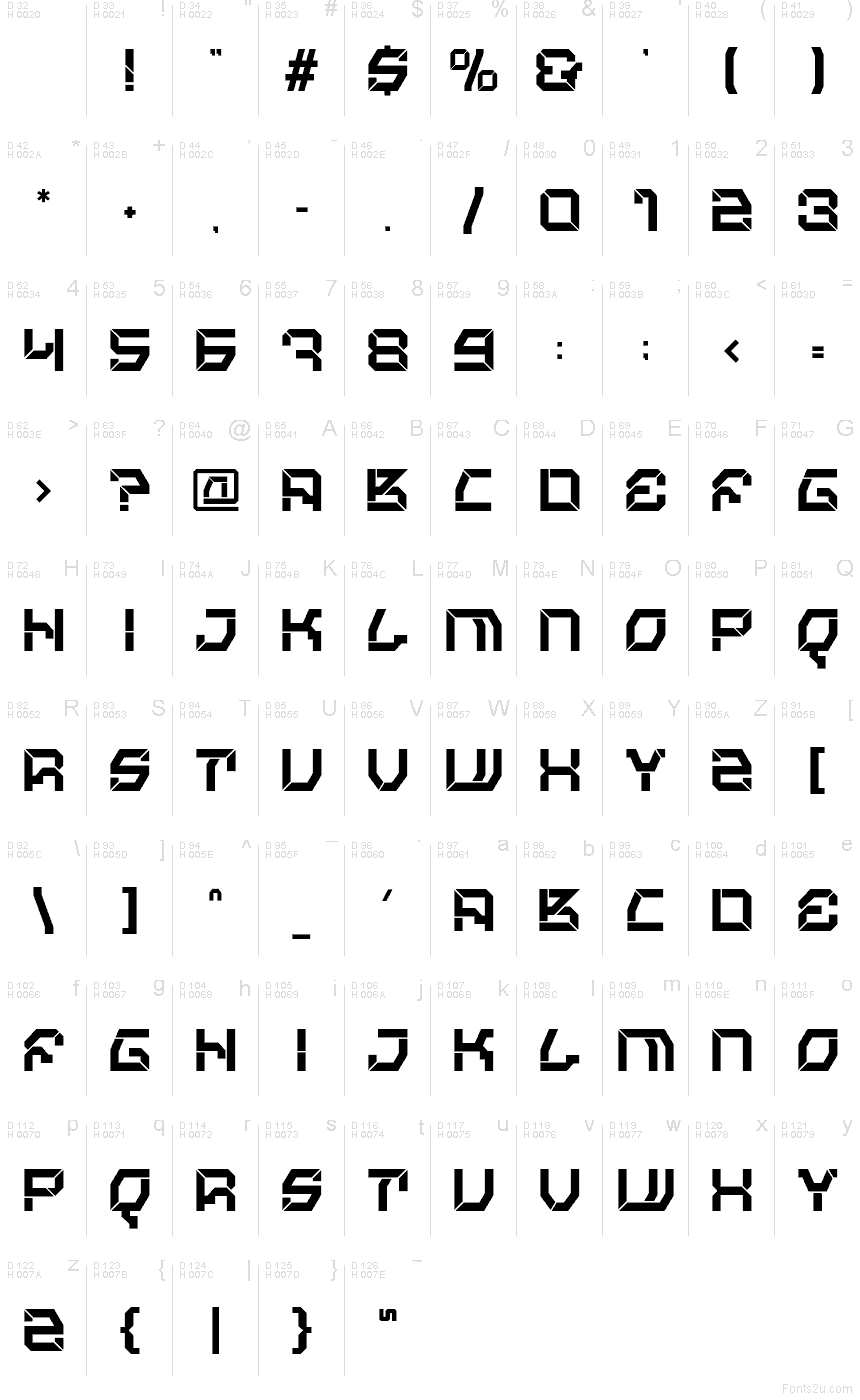
تعد خط Spectra Volt من إنتاج Putracetol Studio خطاً مستقبلياً مجانياً مخصصاً للعناوين، يتميز بكتل مستطيلة صلبة وزوايا مقطوعة بشكل قطري تمنح الحروف إحساساً بأنها صممت ضمن نظام معياري دقيق. هذا التكوين المتكرر يخلق إيقاعاً كهربائياً وحاداً في جميع أنحاء التصميم، مما يبتعد عن أسلوب الخيال العلمي التقليدي ليتجه نحو جماليات لوحات الإرشاد التقنية وخطوط القوالب.
يتمتع هذا الخط بحضور قوي يناسب عناوين الألعاب، وعلامات الرياضات الإلكترونية، وأغلفة الألبومات، وعناوين الملصقات، ورسومات الواجهات حيث تتطلب المفاهيم صوراً ظلية زاوية حادة. كما أن زواياه المقطوعة وأشكاله المدمجة تجعل منه خياراً ممتازاً للتغليف وتراكبات البث المباشر، خاصة عندما ترغب في أن تبدو الكلمات القصيرة مصممة بدقة تقنية بدلاً من أن تكون مجرد كلمات صاخبة.